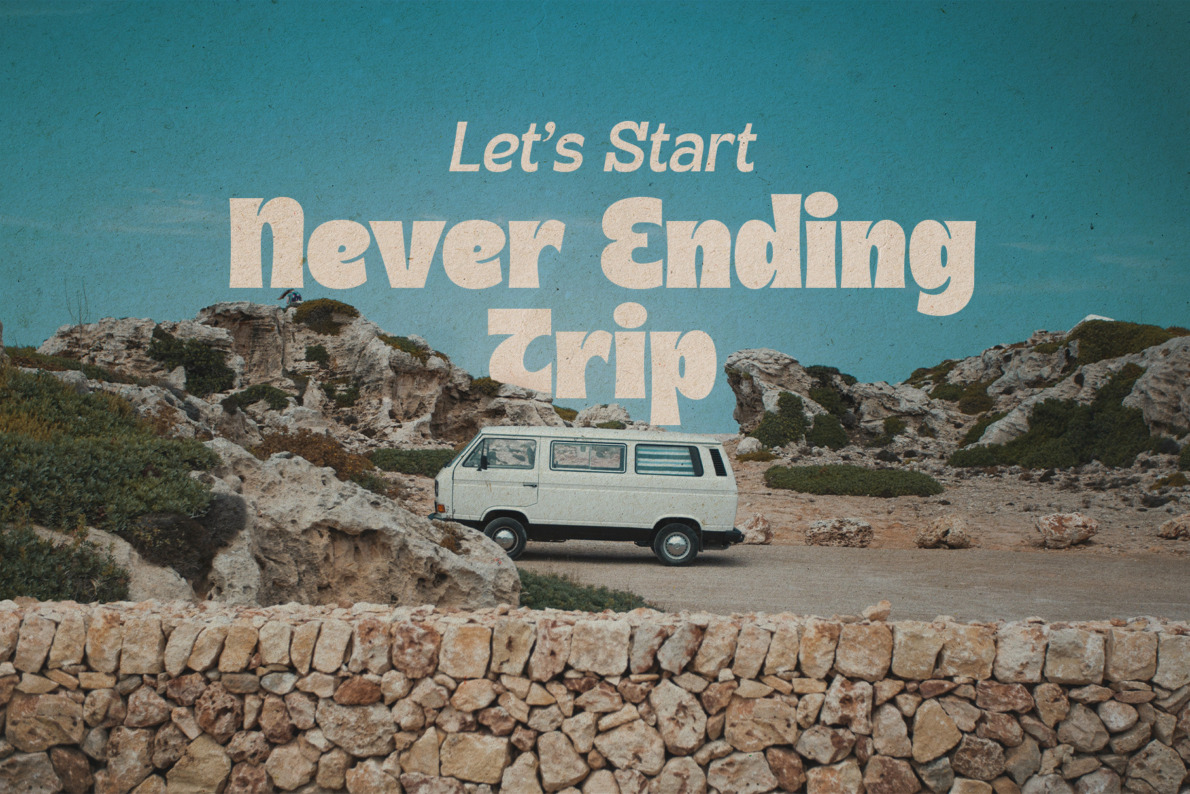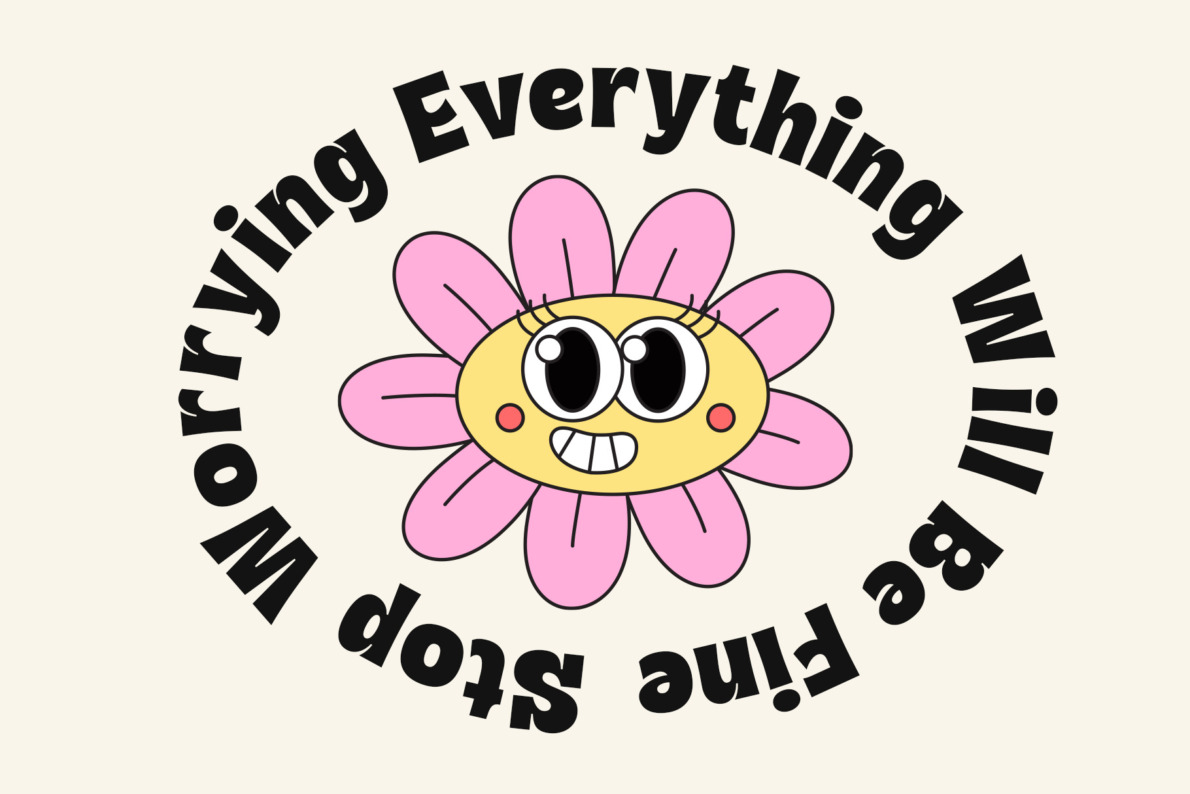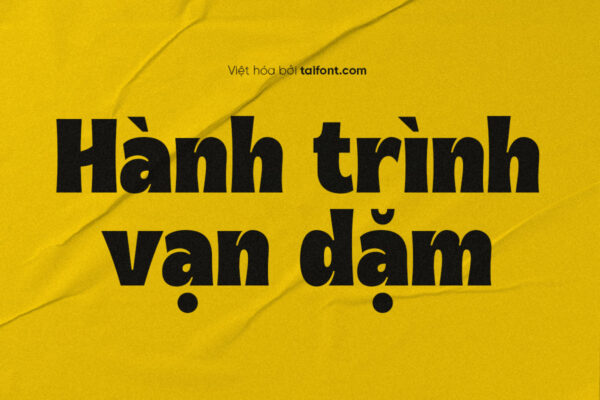
Font Việt hóa TF Gilton Bold là một font chữ không chân nét dày dặn, phù hợp cho thiết kế ẩm thực, tiêu đề lớn
Font Việt hóa TF Gilton Bold – Font ẩm thực, tiêu đề